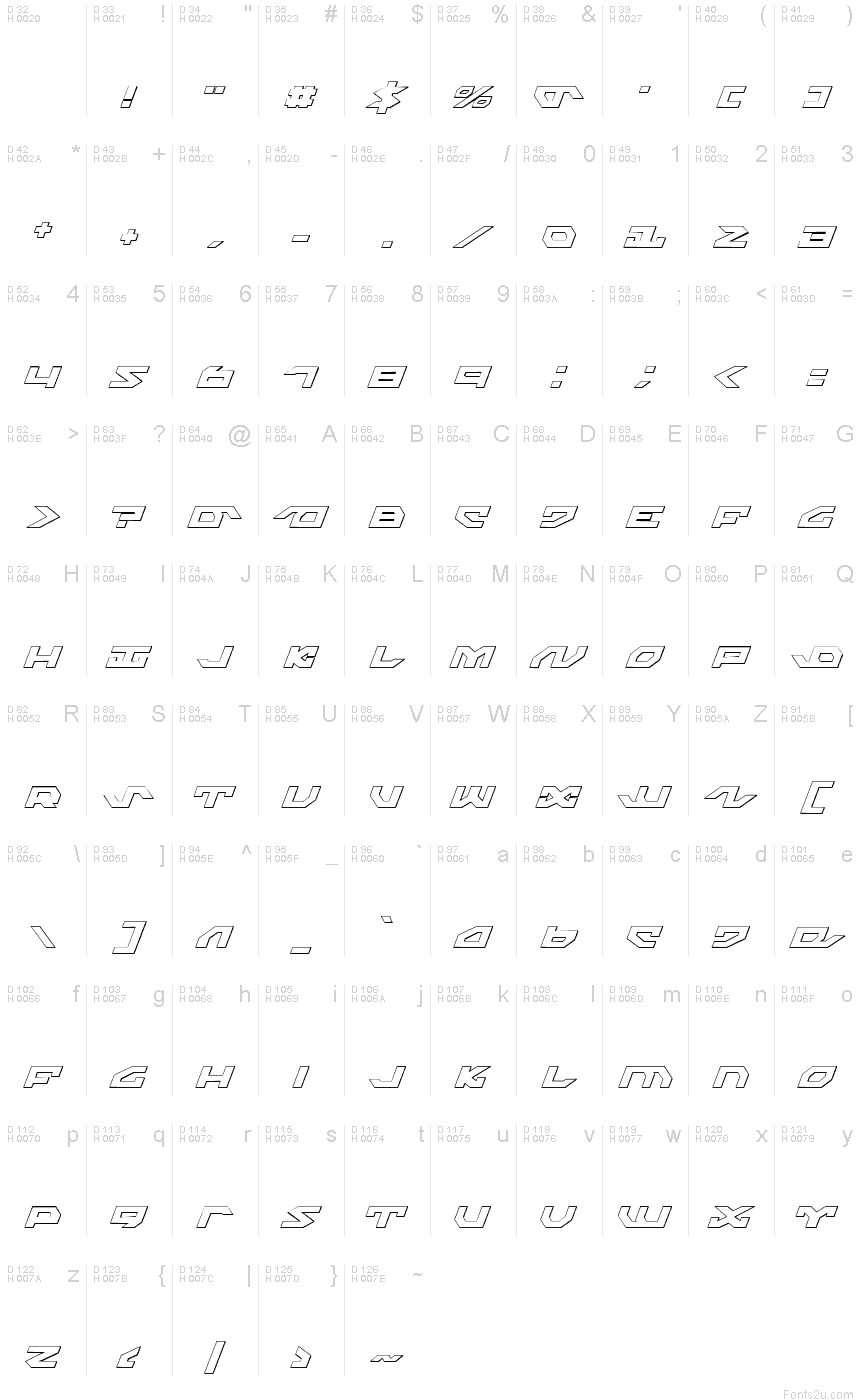
Nightrunner Shadow Italic di Iconian Fonts è un font display futuristico gratuito, caratterizzato da un'inclinazione dinamica che ricorda l'era arcade. Le lettere sono costruite con contorni ampi e angolari e una doppia ombra che conferisce al lettering un aspetto fluttuante, come se fosse tagliato a macchina; lo stile si avvicina molto più al branding sci-fi che a una normale grafica display.
Si adatta perfettamente a loghi di giochi, titoli di poster, copertine di album, grafiche per streaming e cartelli di titoli, dove serve un font gratuito che trasmetta velocità e un pizzico di drama retro-tech. Dato che le maiuscole sono inclinate in avanti con quell'ombra stratificata che le attraversa, funziona bene anche per titoli brevi e monogrammi che cercano un look compatto e sintetico.
Nightrunner Shadow Italic, di Iconian Fonts, è un font display gratuito con contorni in stile corsivo.
Le maiuscole sono costruite con pannelli angolari e includono un secondo contorno sfalsato che crea un netto effetto ombra. Il design presenta una forte inclinazione diagonale.